Выбор идеального шрифта для заголовков — это один из самых важных этапов в работе над дизайном сайта. Очень важно учесть все факторы, которые влияют на восприятие шрифта, — легкость чтения, визуальная иерархия, универсальность и сочетание шрифтов между собой.
В 1-ой части нашей статьи мы рассказали вам о том, что такое шрифт для заголовков, а также дали несколько советов по выбору. В этой статье мы рассмотрим самые знаменитые заголовки и их шрифты, а также расскажем, как легко можно выделить ваш заголовок на сайте.
Журнал Vogue в своем логотипе и заголовках использует культовый шрифт Didot. Этот классический высококонтрастный шрифт с засечками, созданный Фирмином Дидо, воплощает в себе элегантность, изысканность и утонченность. Didot — это идеальный выбор для публикаций на тему мода и стиля.
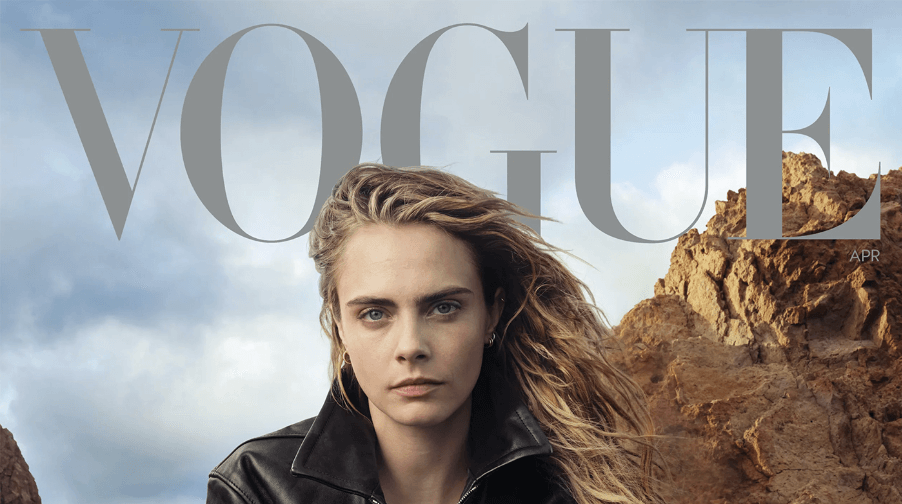
Журнал Rolling Stone использует специальный шрифт Rolling Stone Display для своих заголовков. Этот смелый сжатый шрифт без засечек создан Тобиасом Фрер-Джонсом. Он отлично передает острую, современную и вдохновленную рок-н-роллом эстетику журнала.
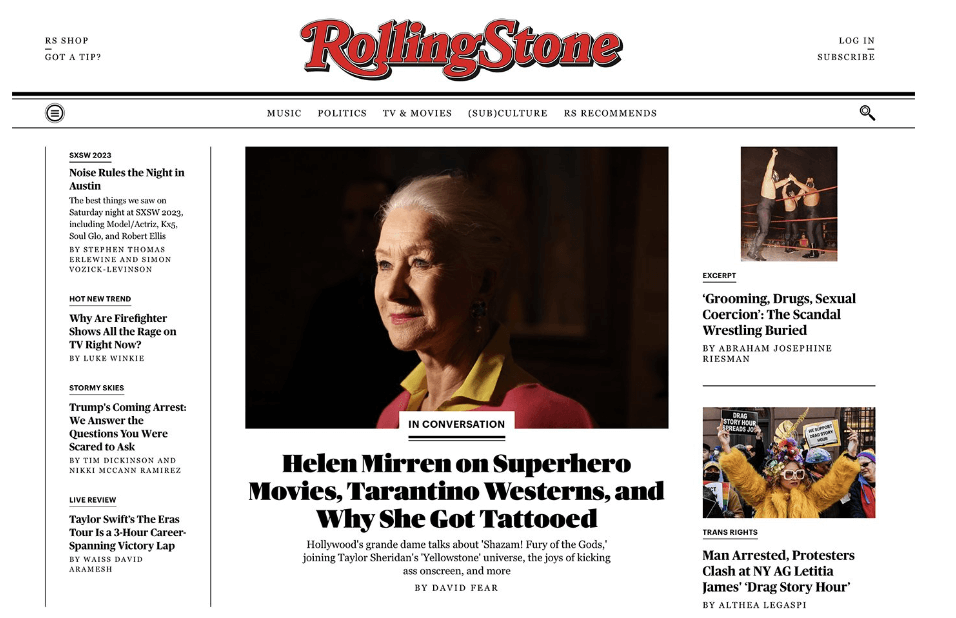
Apple Inc. чаще всего использует шрифт Myriad Pro для заголовков и маркетинговых материалов. Этот чистый современный шрифт без засечек разработан Робертом Слимбахом и Кэрол Твомбли. Он воплощает в себе минималистичную философию дизайна Apple.
Используйте контраст и цвет, чтобы ваши заголовки выделялись на фоне и среди остальных элементов. Выбирайте цвета, которые дополнят ваш дизайн, а текст при этом останется разборчивым и легко читаемым.
Выбирайте достаточно крупный размер шрифта для того, чтобы привлечь внимание пользователей. Но будьте аккуратны — очень важно не перегрузить дизайн вашего сайта слишком массивным заголовком.
Чтобы заголовки выделялись и легко читались, окружите их пустым пространством. Это создаст ощущение баланса и гармонии в вашем дизайне, а также поможет направить внимание пользователей на самую важную информацию.
Поддерживайте согласованность в выборе шрифтов и цветов на протяжении всей работы над дизайном. Это установит четкую визуальную иерархию и поможет пользователям лучше усвоить информацию на сайте.
Старайтесь не перегружать заголовки большим количеством элементов или сложным оформлением, например, тенями или градиентами. Вместо этого уделите внимание выбору яркого и привлекающего внимание шрифта, а также четких, кратких и содержательных формулировок для ваших текстов.